2022 MyFonts Fuente Tendencias que los diseñadores pueden utilizar este año
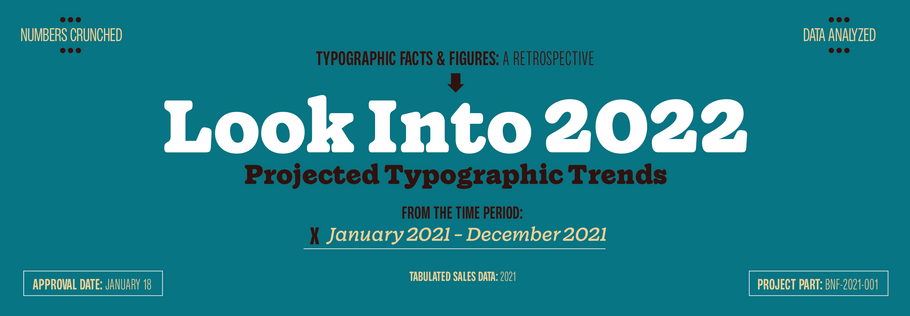
El año pasado, la guía "Type Trends" trató sobre la creación de sorpresas tipográficas, los diseños a medida fuentes, el uso de tipos de letra evocadores para contar una historia y la fusión de arte y tecnología. En cuanto a los tipos de letra, los guiones desenfadados, los diseños industriales sin gracias y los tipos pesados para pantallas ocuparon los primeros puestos en las listas de popularidad.
¿Qué tipos de letra estarán de moda en 2022? Hemos investigado las fuentes que han sido tendencia en las últimas semanas, hemos echado un vistazo a los ganadores de varios concursos de diseño tipográfico y hemos hablado con los expertos tipográficos de MyFonts, para que nos ayuden a responder a esta pregunta.
Esto es lo que se nos ha ocurrido. Las tendencias tipográficas en 2022 serán:
- Resurgimiento de los diseños clásicos sin gracias
- Nuevo interés por el barroco fuentes
- Tipos de letra de dibujos animados
- Nuevos tipos de letra con gracias, amables y francos
- Los tres tipos de guiones ganan popularidad
- Variable fuentes mantiene su tendencia
Fuente Tendencia nº 1: Sans clásica
Aunque parece que cada día aparecen nuevos tipos de letra sin gracias, los clásicos tradicionales no sólo siguen siendo los más vendidos, sino que también están empezando a experimentar un repunte en su uso. ¿Por qué? Porque estos diseños son capaces de satisfacer prácticamente cualquier necesidad tipográfica, son fáciles de recomendar a los clientes de branding y varios se han actualizado con numerosas mejoras.
Diseños como Clásico Grotesco y Futura® Now infunden el porte de los diseños originales con la estética del sigloXXI. Helvetica® Now y Trade Gothic® Next son diseños clásicos actualizados para las necesidades de la imagen moderna. ITC Avant Garde Gothic y Avenir® Next son familias geométricas sin gracias que abordan la ética del diseño de formas muy diferentes. Mientras que Proxima Nova™ tiende un puente entre tipos de letra como Futura Now y Classic Grotesquecombinando proporciones modernas con un aire geométrico.
Fuente Tendencia nº 2: Ornamentado
Se trata de diseños adornados con franjas extravagantes, trazos de caracteres sensuales, entrelazados demostrativos y formas de caracteres ornamentadas. Puede que no destaquen en la escala de legibilidad, pero seguro que atraen la atención, crean marcas denominativas memorables y construyen titulares que son un deleite visual. Son las flores de los jardines de fuente y alegran fácilmente una página que de otro modo sería aburrida.
Sea Angel, Granate y negro y Sunbest Mora son creaciones deliciosamente complejas. Tienen suficientes caracteres alternativos, diseños de barra y ligaduras para crear titulares, marcas denominativas y envases llenos de vida. También hay diseños más discretos, como Kindred, un divertido diseño sin gracias sólo en mayúsculas, que incluye un montón de caracteres alternativos. Piense en un fedora con una pluma alegre. ITC Ziggy es en parte Art Nouveau, en parte psicodélico de los 70 y 100% divertido. En Iniciales ornamentadas son tres conjuntos de letras mayúsculas decorativas fuentes que animan una página, introducen párrafos e incluso sirven como ilustraciones gráficas.
Fuente Tendencia nº 3: Tipos de letra de dibujos animados
Los dibujos animados fuentes parecen salidos de un cómic o una novela gráfica. Tienen un aspecto dibujado a mano, una estructura informal y, la mayoría de las veces, una disposición caprichosa. caprichoso. Están de moda porque aportan un aire humano y desenfadado a los titulares y a los bloques cortos de texto. La popularidad de este diseño se debe a sus cualidades cálidas, amistosas y desenfadadas, que todos anhelamos hoy en día. Estos fuentes también pueden añadir impacto a un titular y un poco de humanidad a bloques cortos de texto.
La Caricatura Pétrea del Vino no es precisamente adorable. Pero eso demuestra que los tipos de letra pueden ser camaleones gráficos que se adaptan fácilmente a diversos entornos. Coloque Wine Stony Cartoon en tamaños pequeños y sus bordes ásperos desaparecerán. Póngala grande en un color agradable y tendrá un poco de encanto terrenal. Niños fantasma y Bejo son diseños de tallas grandes imponentes y accesibles, mientras que el PH tiene suficientes pesos, proporciones, iconos útiles y banners de palabras para llenar un contenedor de transporte.
Fuente Tendencia nº 4: Tipos de letra con gracias distintivas
Aquí no hay copas de cristal. Estos tipos de letra no son contenedores transparentes de contenido textual. (Demasiado para el consejo de Beatrice Warde.) Son fuentes que hacen una declaración. Suelen tener un y, al tener gracias, tienen cierta seriedad. Eche un vistazo y encontrará estos diseños, y otros parecidos, en un número creciente de aplicaciones.
El Blacker Pro tiene multitud de variantes de texto y visualización, en proporciones normales y condensadas, además de una veintena de títulos fuentes. Basta con fuentes para que Blacker Pro se adapte tanto a textos largos y contenidos a la carta como a titulares de vallas publicitarias. Cotford™ es una nueva familia de texto elegante y robusto fuentes. Los diseños de pantalla son ideales para marcas, presentaciones editoriales y logotipos, mientras que los diseños de texto de Cotford son ideales para textos extensos impresos y en pantalla. Gazpacho y Imagist son las dos "patas felices" de la lista. Las gracias de Gazpacho son amables y acogedoras, mientras que las de Imagist son amplias y fluidas. Cartel Sweep combina el peso de los diseños antiguos, la elegancia dramática de las Didones del sigloXVIII y un encantador garbo en caracteres como la a, la e y la g, para crear un diseño tan distintivo como atractivo.